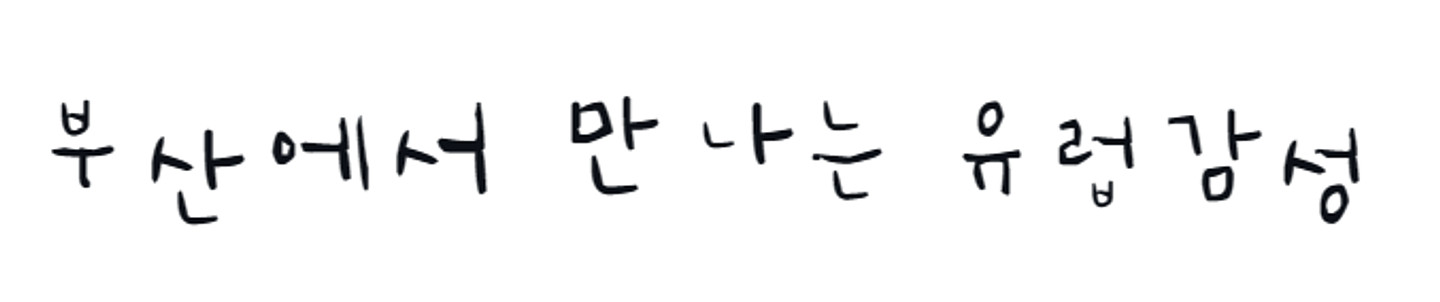
손글씨같은 폰트 궁금해요
손으로 직접 썼을 가능성이 높아보입니다.
'산'과 '만'의 'ㅏ'와 'ㄴ' 등 어느 정도 겹치는 부분이 있는 자음/모음 조합은 제 아무리 불규칙하게 보이는 폰트라도 저렇게까지 하나하나 다 새로 쓴 것처럼 만들지는 않을텐데... (예시로 올리는 이미지의 서체처럼요.) (예시는 솔인써니체입니다.) 올려주신 이미지 속 문장이 특정 폰트로 쓰였을 가능성보다는, 차라리 아이패드+애플펜슬 등의 장비로 직접 썼을 가능성이 더 높아보입니다... 'ㄴ'자만 봐도 저 문장 안에 5개나 들어갔는데 제각각 다 달라요...